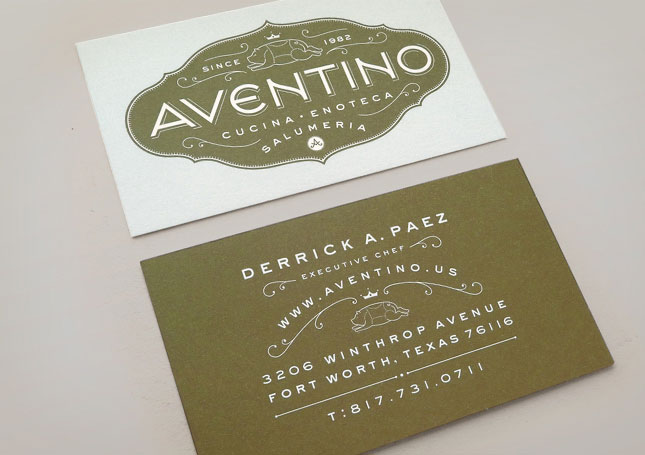
Font für eine Metzgerei
Nun als Neuling hier hätte ich da eine Frage.
Mein Freund, der eine Metzgerei betreibt, bat mich ihm bei der Erstellung eines Flyers für seine Metzgerei und seinen Partyservice zu helfen. :?
Aber Flyer gibt es wie Sand am Meer also soll es nichts so 08/15 aussehen. Meine Frage nun an euch.
Welche Schriftart würdet ihr für eine Metzgerei und Partyservice vorschlagen?
was für schriften hast du denn zur auswahl?
geht es nur um den tet auf den flyer oder geht es um ein logo?
eigentlich reichen die systemschriften für den normalen text,
blickfang kann man auch mit anderen elementen erzeugen,
lesbar sollte der flyer sein – darum würde ich von 'spaßfonts' abraten.
mit der schriftwahl alleine ist es nicht getan.
seit dem ich die schrift SAUNA kenne, denke ich immer wieder daran sie für eine metzgerei einzusetzen aber so einen kunden habe ich leider nicht.
schaue dir die beispiele an.
und hier wäre die schrift zu sehen
Für einen Partyservice wäre es wichtig, dass er so aussieht, dass man diese Leute gerne auf seiner Party hätte, sprich ordentlich, elegant und stilsicher.
Mit diesen Parametern hast du jede Menge Raum, z.B. könnte es so aussehen
Wenn ich meine Lieblingsempfehlung hier nochmal anbringen darf: No jokes with names und beim Firmenschriftzug nicht witzig sein. Also keine Messer, lachenden Schweine oder Buchstaben mit eingezeichneten Kotteletes.